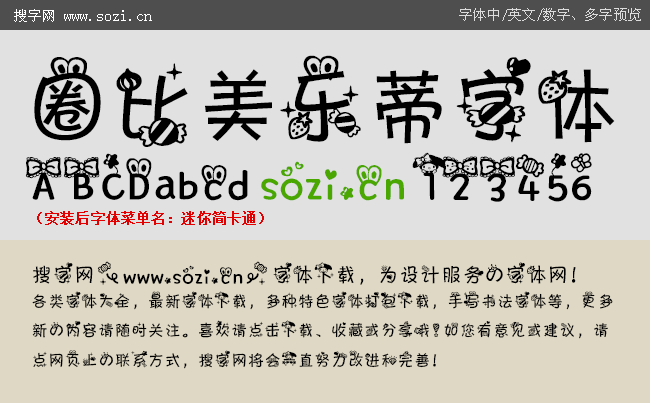
圈比美樂蒂字體
搜字網(wǎng)給大家提供一款圈比美樂蒂字體手機(jī)中文字體下載。這款手機(jī)字體以迷你簡卡通字體為原形,迷你簡卡通在字形設(shè)計上采用了“黑體”的基本筆形,參以行書的筆意、形態(tài),婉轉(zhuǎn)有度,斜正相倚,于傳統(tǒng)美中見時代氣息。這款手機(jī)字體間又嵌入可愛的卡通圖案,非常適合喜歡卡通的朋友在手機(jī)上安裝使用。